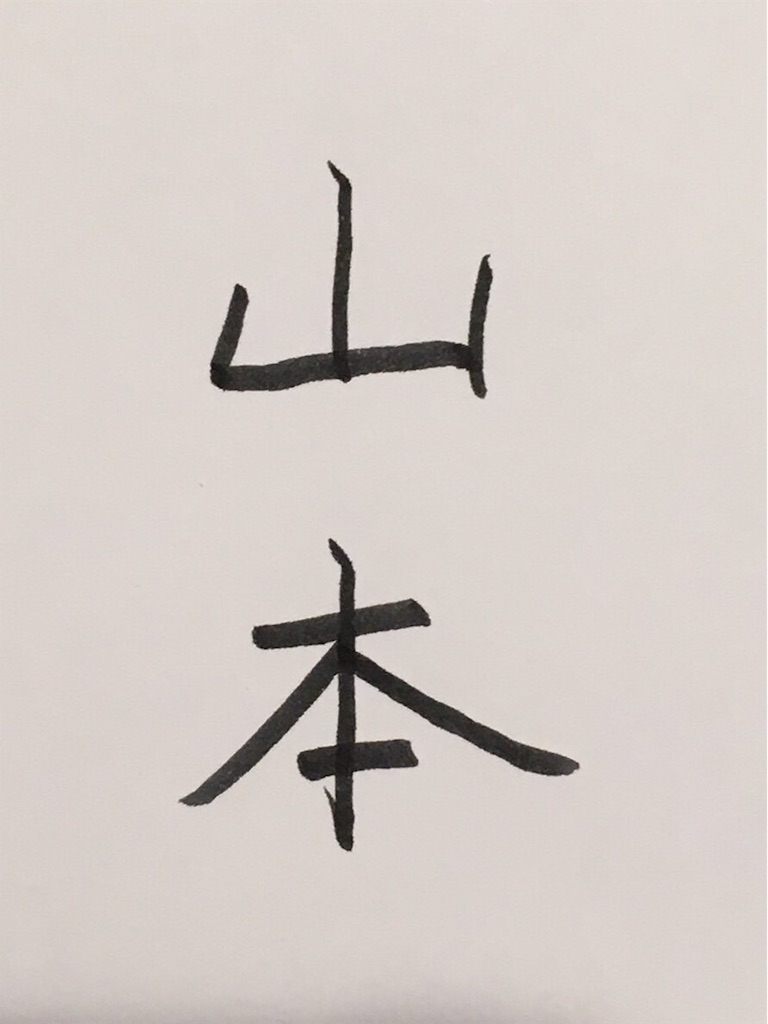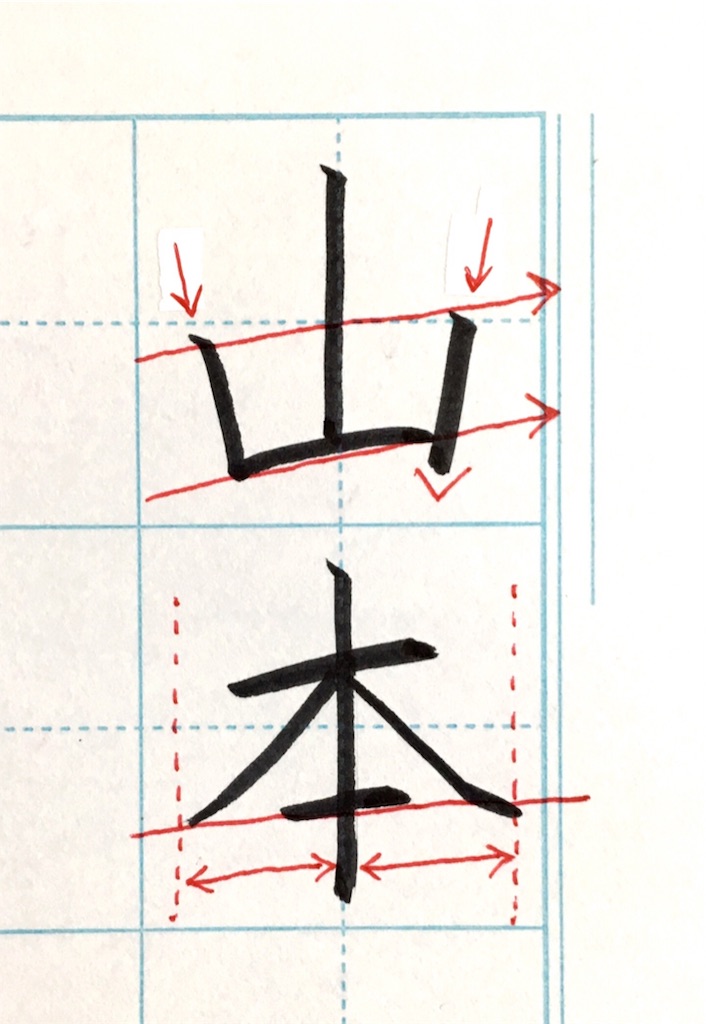
○良いところ
中心がしっかりと通っています。それぞれの文字の大きさも適切です。
◎改善点
【山】の両端の向き、【本】の左右払いの位置が主なポイントです。
↓今回はこんな感じに添削をさせていただきました。
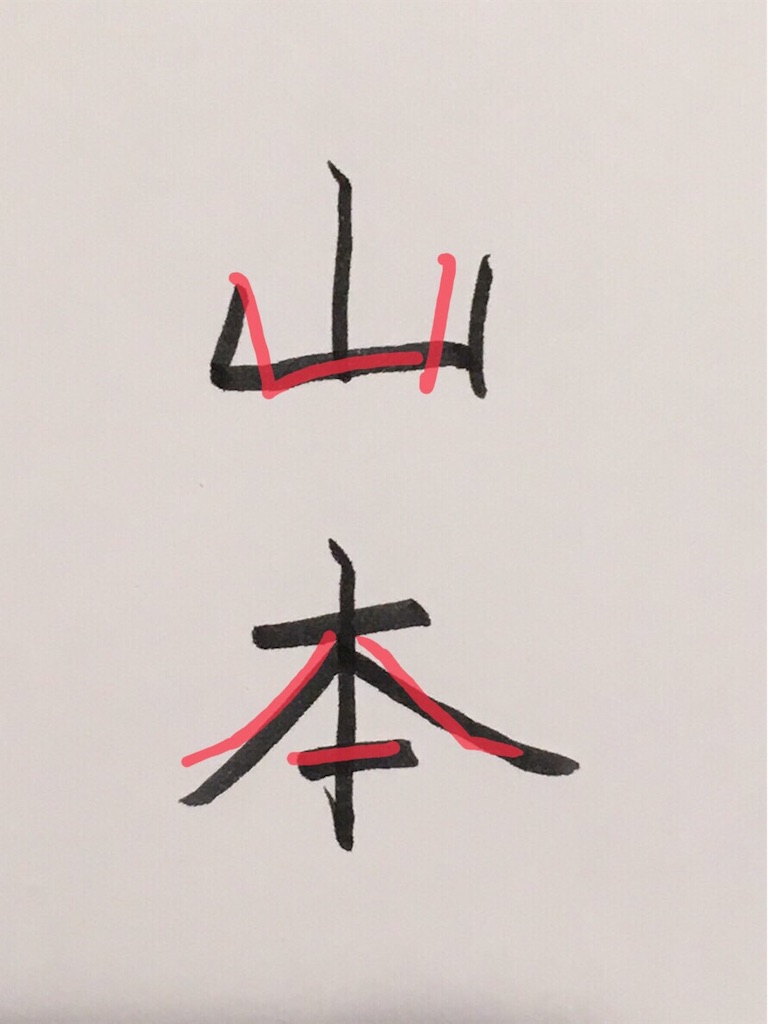
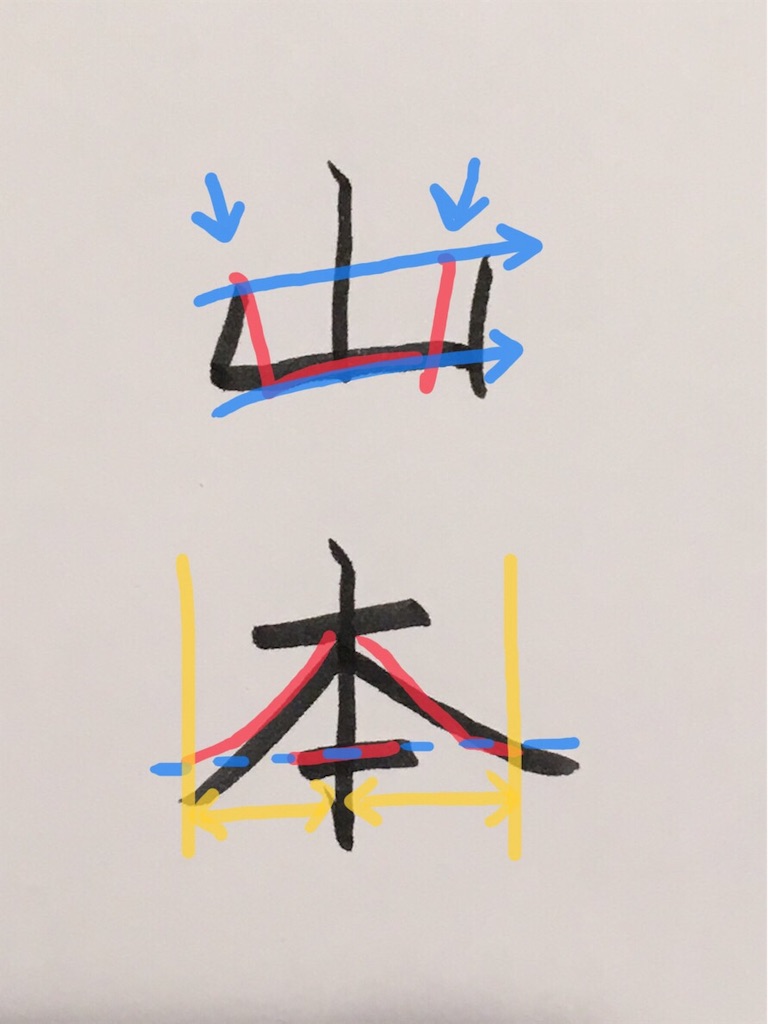
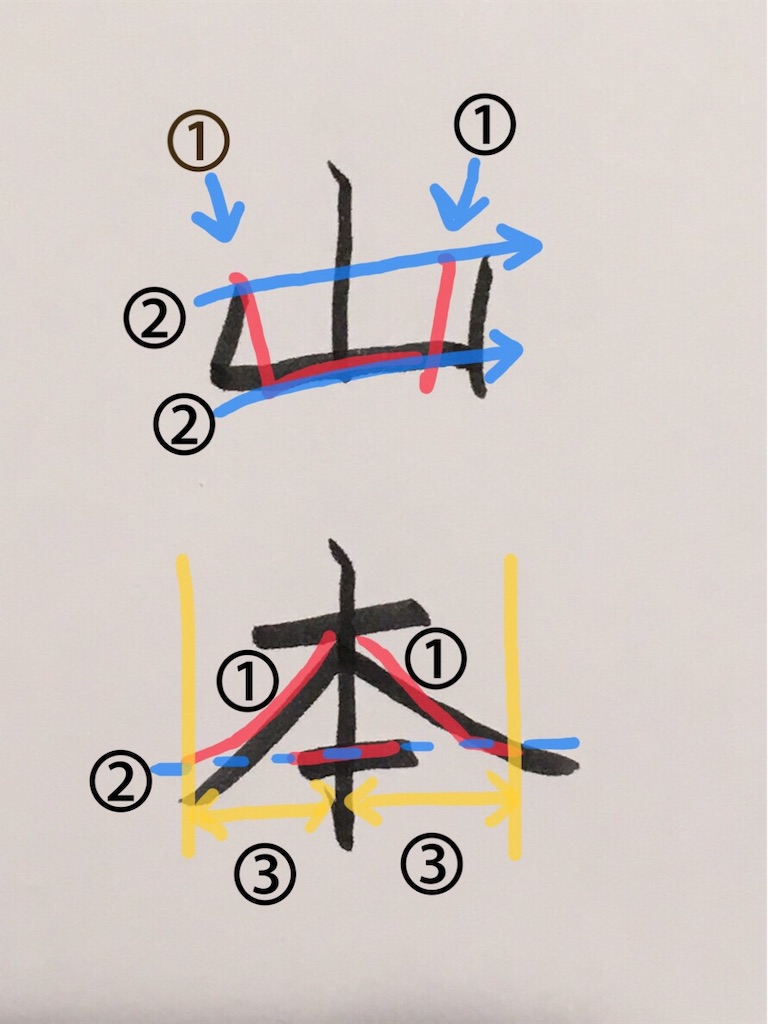
〈山〉
➀両端の縦画は、同じ角度で内向きに。
➁2、3画目の始まりと横画は右上がりでそろえる。
〈本〉
➀払いはそれぞれ1、2画目の交点からスタートすると◎。左払い→5画目→右払いをそろえる。
➁払いの長さを左右同じに。
以上が添削ポイントです。
見本を書いてみました。筆ペンでチャレンジしていただきましたので、質感の近いもので書いています。
△形が分かりやすくするために、マス目を使っていますm(._.)m